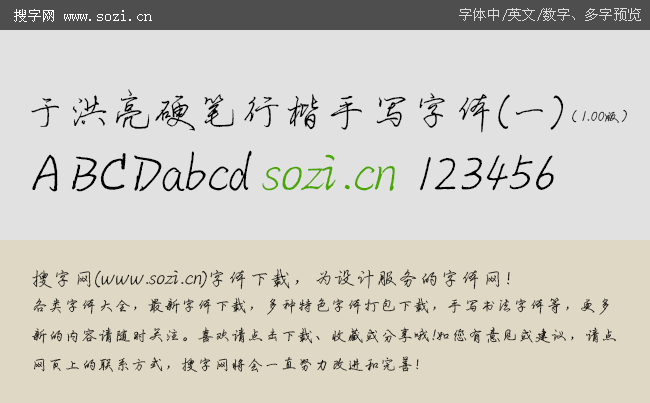
于洪亮硬筆行楷手寫字體(一)
搜字網(wǎng)提供一款于洪亮硬筆行楷手寫字體(一)中文書法字體下載,于洪亮硬筆行楷手寫字體是一款手寫風格的書法字體,字體書寫流暢,字形大方,整體效果十分出色,適合應(yīng)用于廣告設(shè)計、名片設(shè)計、包裝印刷、產(chǎn)品設(shè)計等應(yīng)用。
• 風格類別: 行楷